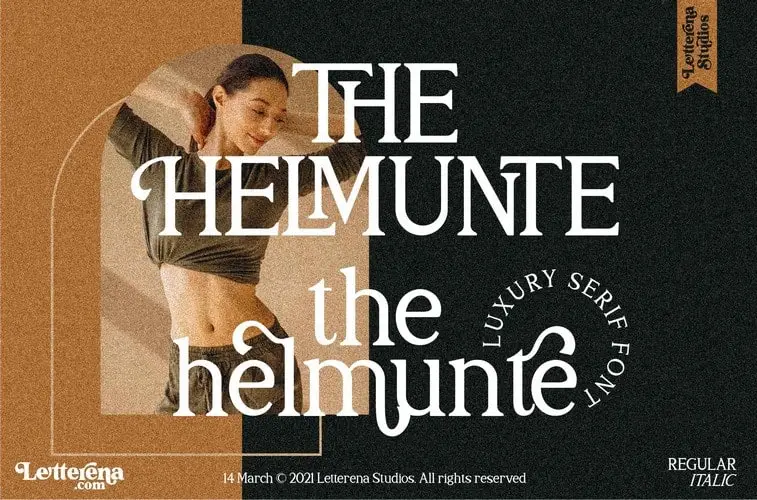
The Helmunte Serif Font – Download Grátis
A Helmunte Serif é uma fonte serif clássica moderna que oferece um toque de sofisticação com linhas suaves e ligaduras belas, além de vários gílitos alternativos especiais e suporte para múltiplas línguas. Ela se destaca em qualquer projeto, seja um logo ou cartão de nome, uma embalagem ou etiqueta, até mesmo um design fotográfico ou watermark. Suited para todos os projetos que exigem um toque de sofisticação elegante e luxuoso, a Helmunte Serif é perfeita para trabalhos como branding, homewares, produtores de embalagens, produtos personalizados, nome cards, cartões de convite, cartões de agradecimento, livros, capas, máscaras, sacolas de shopping e estampas de camisetas. Seja em eventos especiais ou trabalhos que merecem um toque de luxo e beleza, a Helmunte Serif é sua fonte ideal.